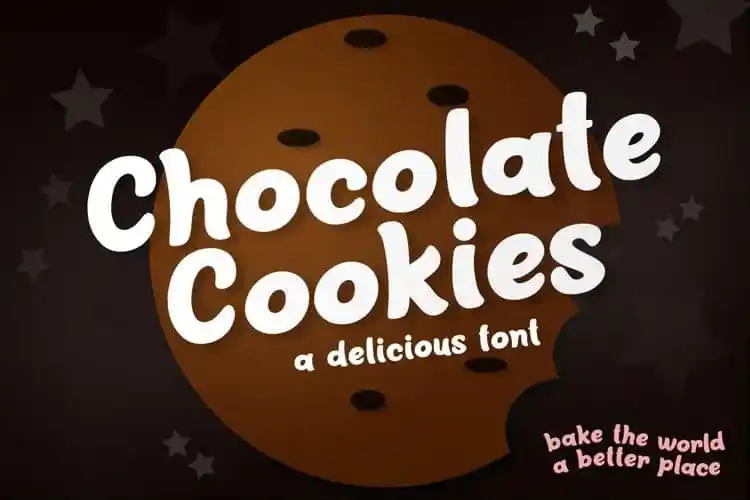
Chocolate Cookies Display Font – Download Grátis
Chocolate Cookies Display Font é uma fonte de exibição que brinca com a delicadeza e a inocência das letras escritas à mão. Desenvolvida pela deedeetype, essa fonte distintiva e arredondada faz dela um verdadeiro trabalho de arte. Perfeita para criações como cartazes, branding, postagens nas redes sociais, merchandising, arte criativa, títulos de livros, folhetos, e muito mais. Essa é uma escolha ótima se você está procurando por uma fonte exibição que traga um toque especial à sua próxima criação visual.